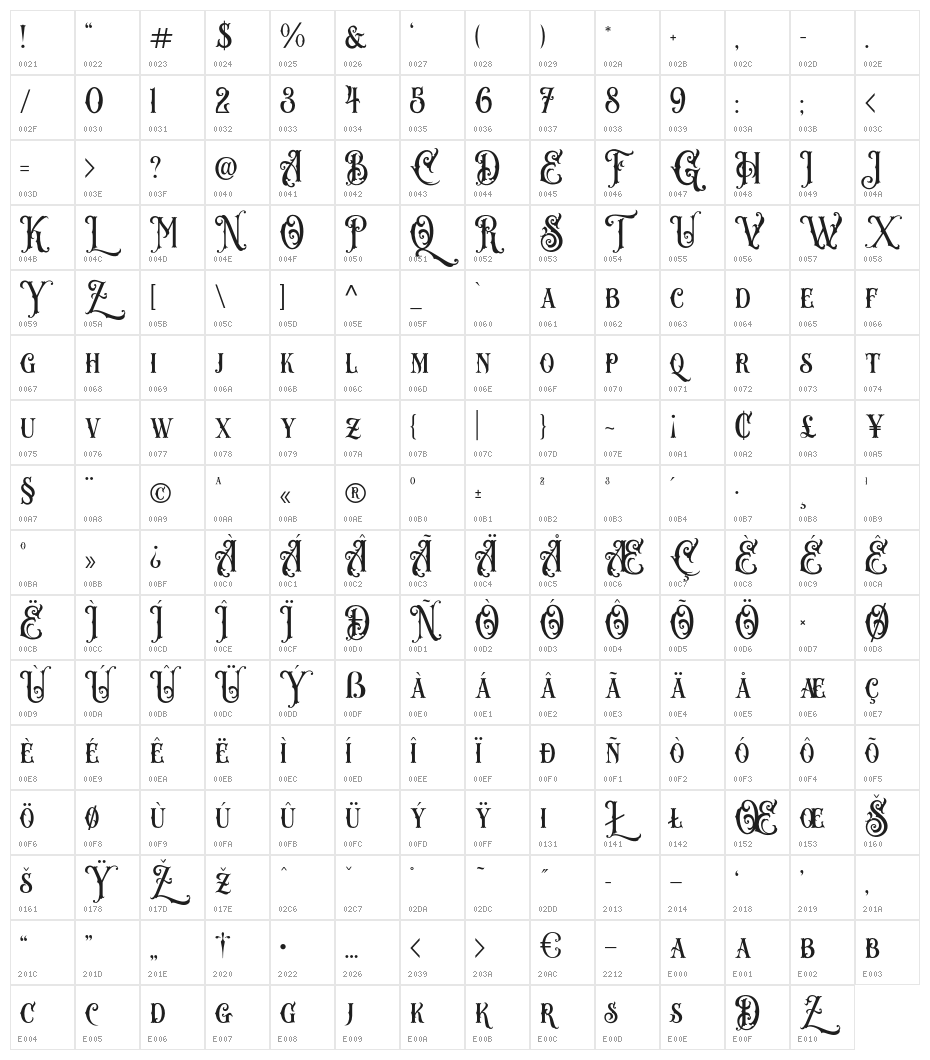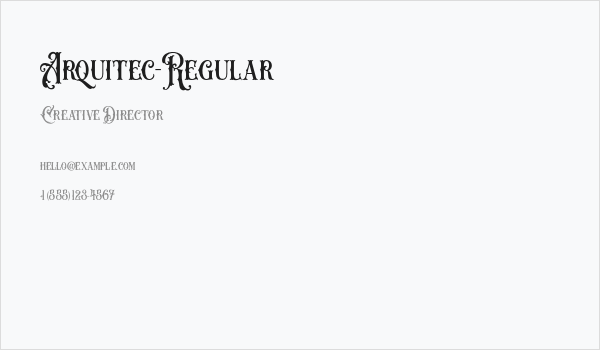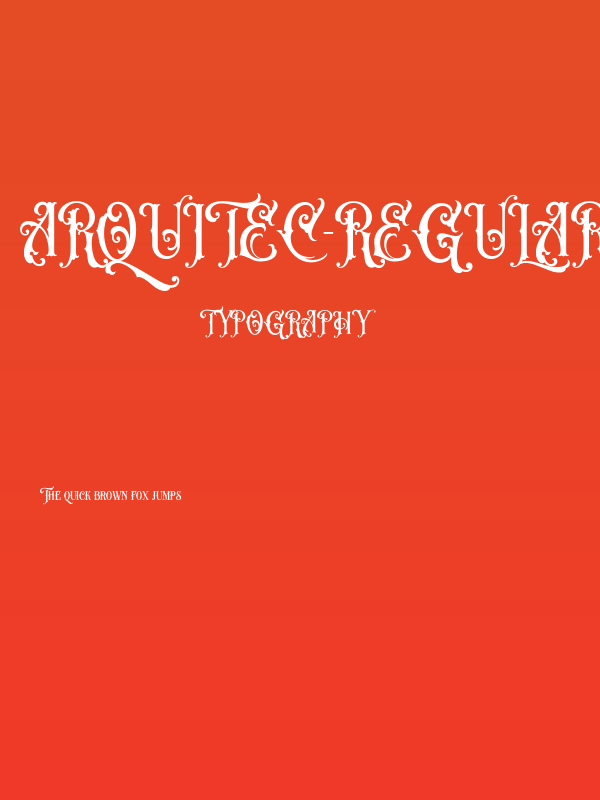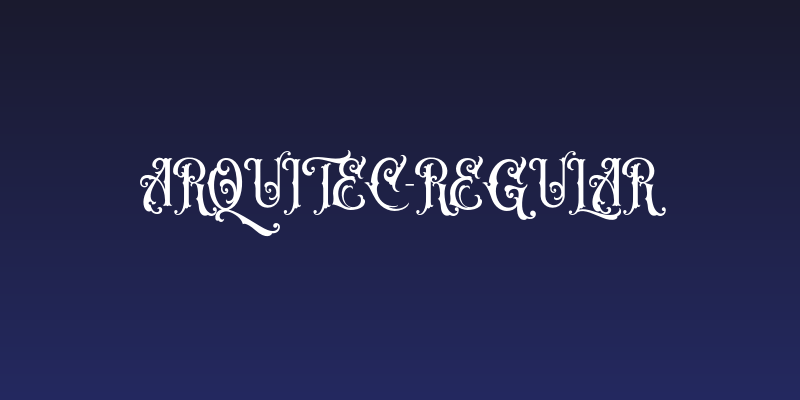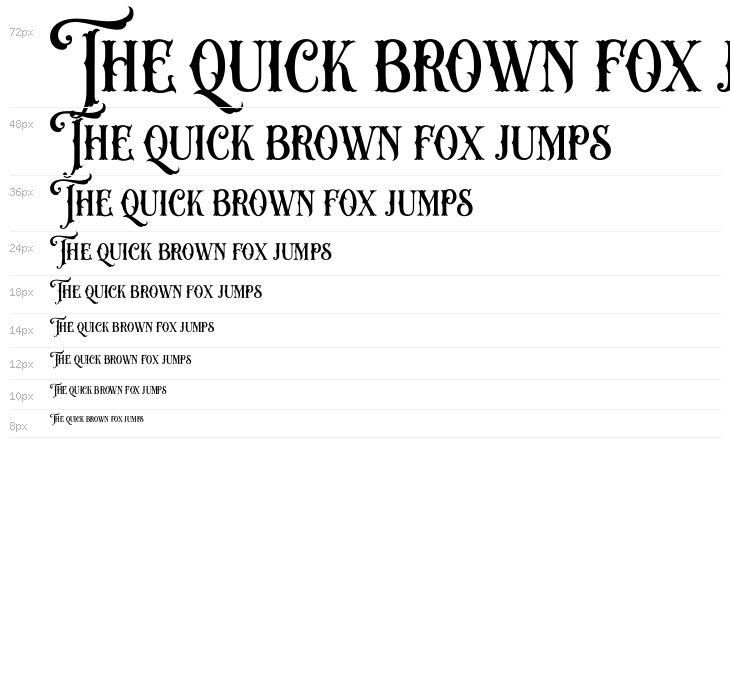
Arquitec-Regular Font
| Anwendungsfall | Headlines, Logos, Artistic displays |
| Vorgeschlagene Projekte | Ideal for wedding invitations, event posters, branding for luxury products, or any project requiring a touch of elegance and sophistication. |